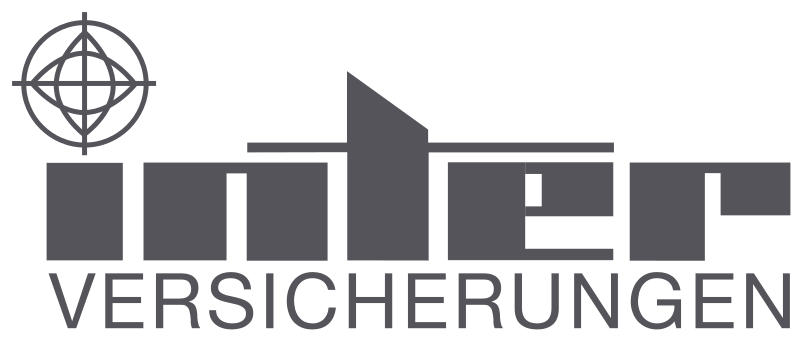
60er/70er Jahre Schrift (in vielen Firmenlogos)
wer kennt diese Schrift?
Hab sie schon in vielen Firmenlogos gesehen, speziell in denen von Bauunternehmen aus den 60ern und 70ern.
Die quadratische Schrift für das Logo ist sehr wahrscheinlich handgemacht. Diese konstruierten Buchstaben in Logos haben aber eine viel ältere Geschichte und gehen bis mindestens 1900 zurück. Siehe auch:
Das Wort „VERSICHERUNGEN” ist in einer Helvetica gesetzt.